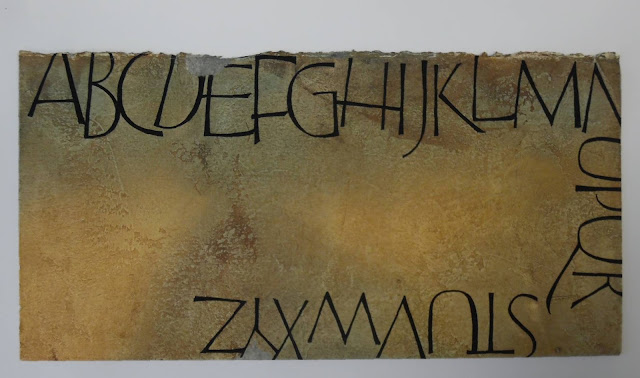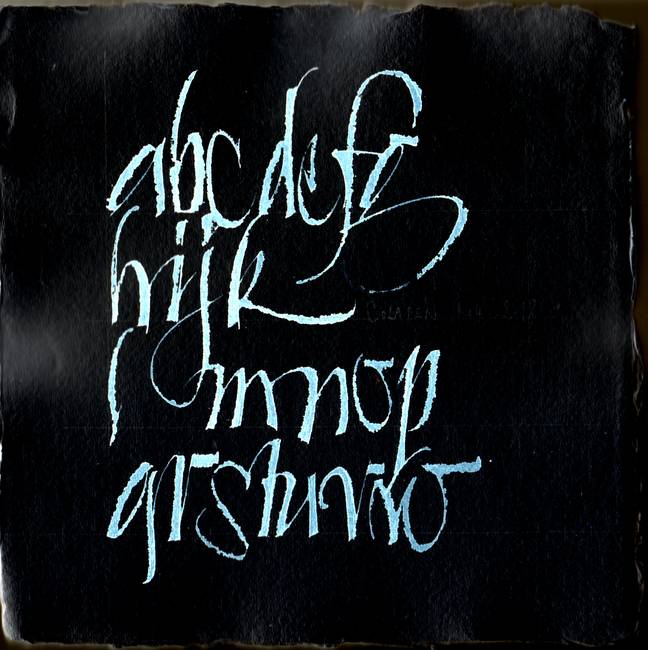
EXPOSITION : D'Argoat en Armor
Tableau illustrant l'affiche :
Espace subjectif 9, 86 x 80
Bien que plus proche de l'abstraction que la figuration, ma peinture est nourrie des paysages marins et terrestres qui m'entourent. Le titre de l'exposition est inspiré d'une rubrique du Télégramme de mon enfance - d'Armor en Argoat- qui m'a fait comprendre la double identité du territoire où je grandissais : la mer comme frontière et la terre, le végétal à l'intérieur, reliés par l'eau.
Les tableaux que j'ai choisis ont été réalisés sur une vingtaine d'années . Ils appartiennent à différentes séries : Espaces subjectifs, Végétalis, Autres lieux, Grammaires blanches...etc et deux tableaux calligraphiques.
Cette année, je propose un stage intitulé "Ecriture de carnets". Je propose l'apprentissage d'une petite écriture inspirée de la chancelière, stylée, lisible et personnalisable pour écrire dans vos carnets. Carnets de voyage, album de haïku, carnet de citations, artist journal.... Les outils utilisés sont ceux du dessinateur : stylo-plume Platinum, fineliner 0,3 et stylomine bic. Le stage s'adresse aussi bien à des non-calligraphes qu'à des calligraphes de tous niveaux.
STAGE COMPOSITION ART NOUVEAU 4 JOURS : THE SEQUELS
Nous avons passé quatre jours en résidence aux Gîtes de Kerzont dans les côtes d'Armor sur le thème de la Composition Art nouveau.
Après  un apprentissage collectif des formes Ver Sacrum à la plume palette finalisé par une petite composition format A4, je proposais un parcours plus individuel. Les stagiaires avaient la possibilité soit de travailler plusieurs écritures et de réaliser un album de calligraphie soit de s'engager sur une composition plus importante.
Le travail calligraphique tenait en trois propositions : une entrée par l'outil  -pinceau plat, pinceau pointu en mouvement - , ou bien un travail de dessin de lettre - au pinceau pointu "sculpteur" ou au fineliner à partir de squelettres engraissées ou encore l'appropriation d'écritures historiques - "Paradies" de Koloman Moser et "Roycroft" de Dard Hunter. L'entrée par l'outil a été privilégiée.
La documentation mise à disposition - beaux livres, portevue d'images - a aussi permis de prendre conscience de l'étendue de l'univers graphique Art nouveau  et de l'espace de jeu calligraphique possible.
1. Dard Hunter Graphic works - style Roycroft
2.Fac-similé de la revue Die Fläche
3. Des extraits significatifs de la revue Ver sacrum
J'organise à nouveau un stage en résidence aux Gîtes de Kerzont l'année prochaine, du lundi 25 au jeudi 28 octobre 2027. Le thème choisi est : Linocalli. Linogravure de lettres dessinées, gravées et imprimées sur papier fin, intégrées à une composition sur papier enduit. C'est un stage que je suis allée animer dans le Tessin suisse, à Lugano, au printemps dernier. Si vous aimez croiser les techniques...
Sur les deux images qui viennent, la structure dessinée est la même. Les couleurs, les contrastes et les lumières tirent la réception de cette image vers le figuratif ou l'abstrait.
Ci-dessous, deux compositions sur deux formats double-carré horizontaux :
Tiers du bas et tiers du haut :